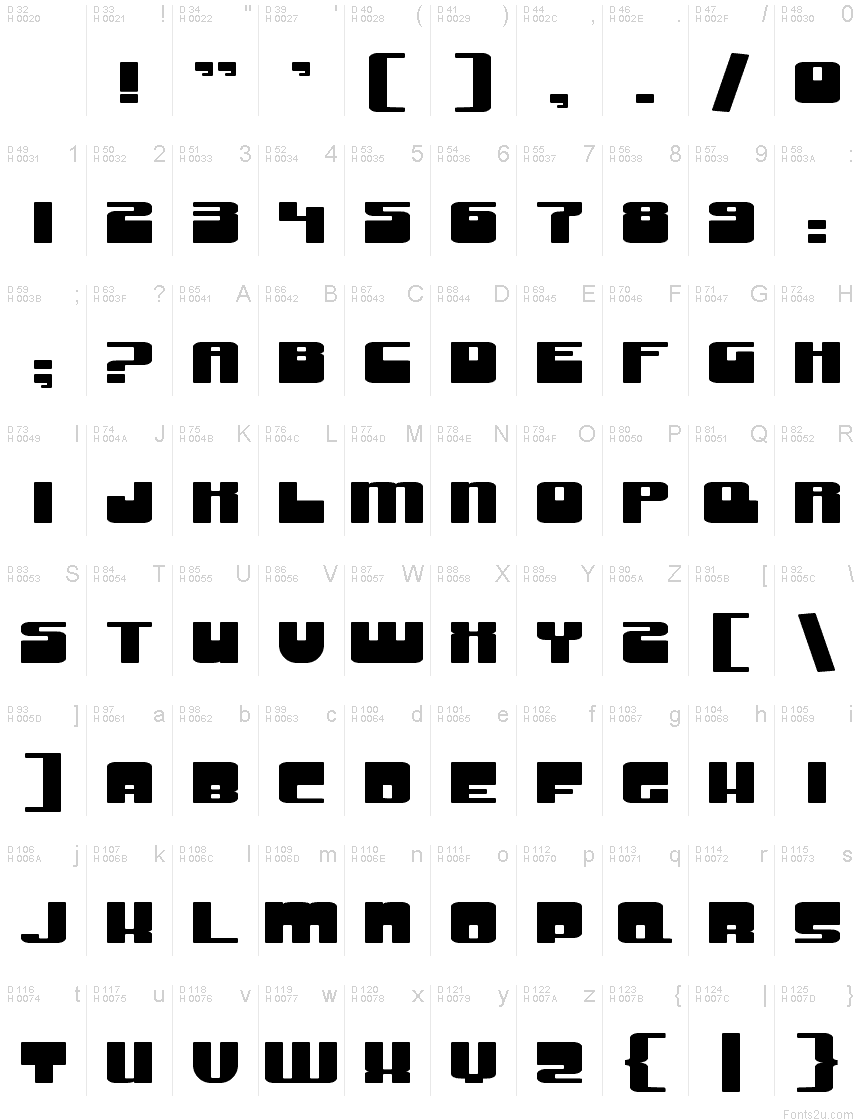
Groove Machine Exp Upright od Shywedge to darmowy, groovowy krój displayowy o odważnym, klockowatym charakterze, który przenosi wprost na parkiet lat 90. Szerokie, kwadratowe formy i mocno wypełnione wnętrza liter tworzą solidny rytm, przywodzący na myśl napisy wytłoczone na błyszczącej kasecie. Zaokrąglone rogi wystarczająco łagodzą tę masywność, dzięki czemu całość wydaje się zabawna i przystępna, a nie surowa czy industrialna.
Groove Machine Exp Upright sprawi, że Twoje nagłówki na ulotkach imprezowych, plakatach w stylu retro, tytułach gier arcade, okładkach albumów, miniaturach na YouTube czy w eksperymentalnych logotypach nabiorą energii. Ciasne światło między literami podkręca dynamikę, więc śmiało korzystaj z tego fontu w dużych formatach, a w tekście głównym zestaw go z prostym, geometrycznym bezszeryfem, aby zachować czytelność i idealny rytm.